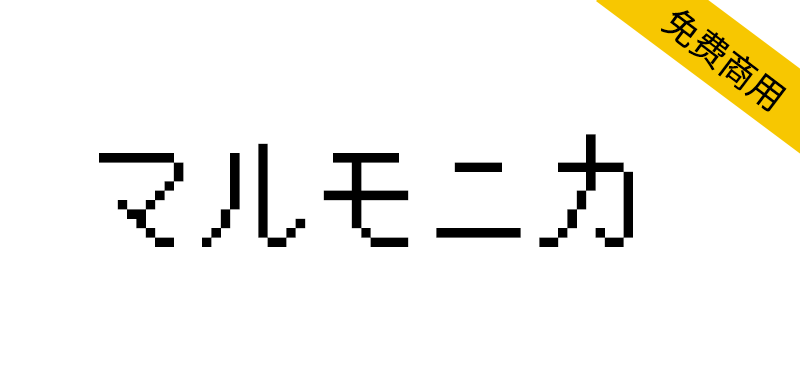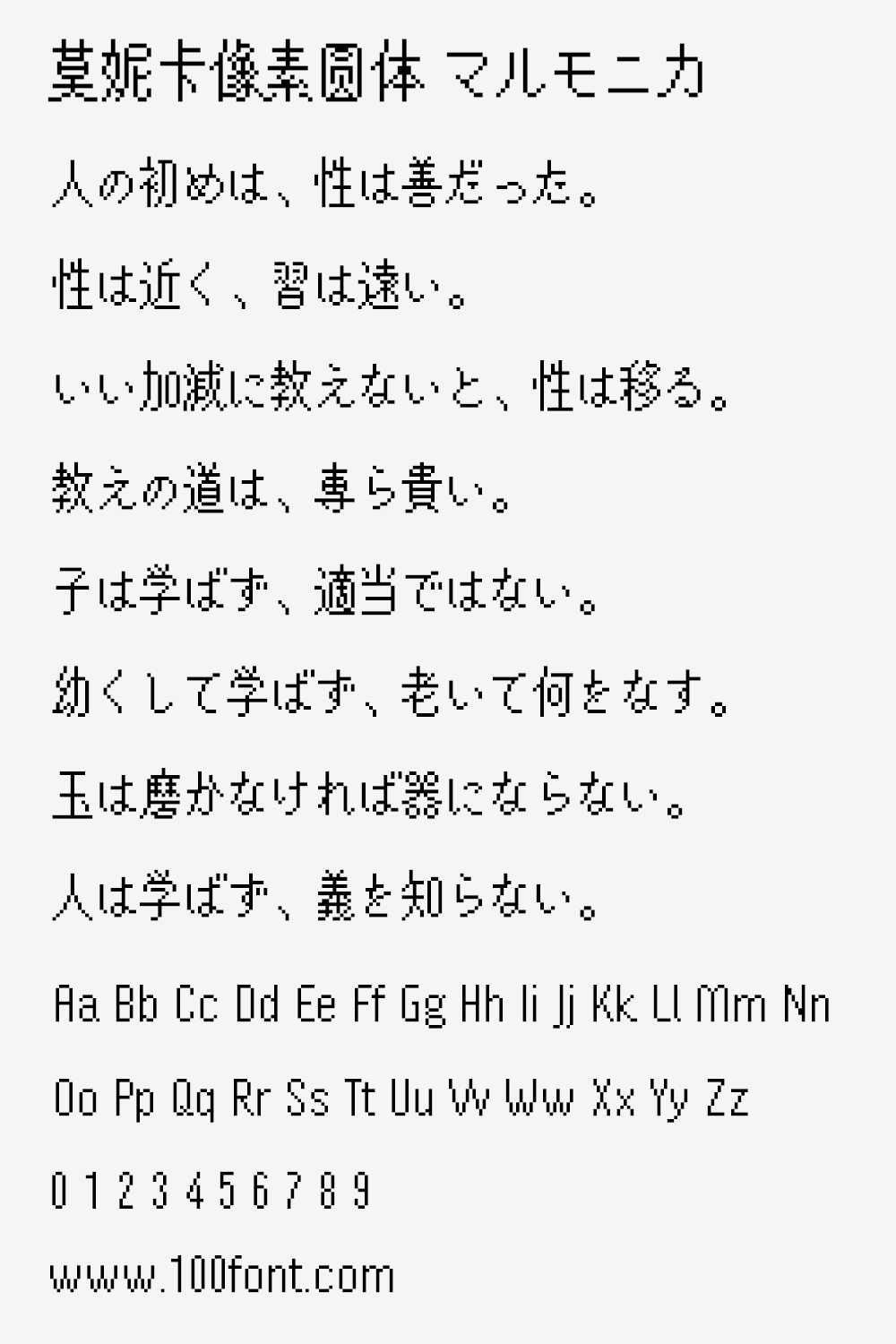
■追求像素形成的曲线美。
是兼具“柔软”和“严肃”的像素字体。
JIS第1水准汉字2965字,第2水准汉字3390字完全收录!
打印标准字体1022字也对应。
■美丽的欧文,充实的多语言对应。
支持使用拉丁文字、西里尔文字的多种语言。
通过独特的字间调节,即使在没有字距调整功能的游戏开发环境中也能实现自然美丽的欧文表示。
■ ピクセルが形作る曲線美を追求。
「柔らかさ」と「シリアスさ」を併せ持つピクセルフォントです。
JIS第1水準漢字2965字、第2水準漢字3390字を完全収録!
印刷標準字体1022字にも対応しています。
■ 美しい欧文、充実の多言語対応。
ラテン文字、キリル文字を用いる多数の言語に対応。
独自の字間調節により、カーニング機能のないゲーム開発環境でも自然で美しい欧文表示を実現します。